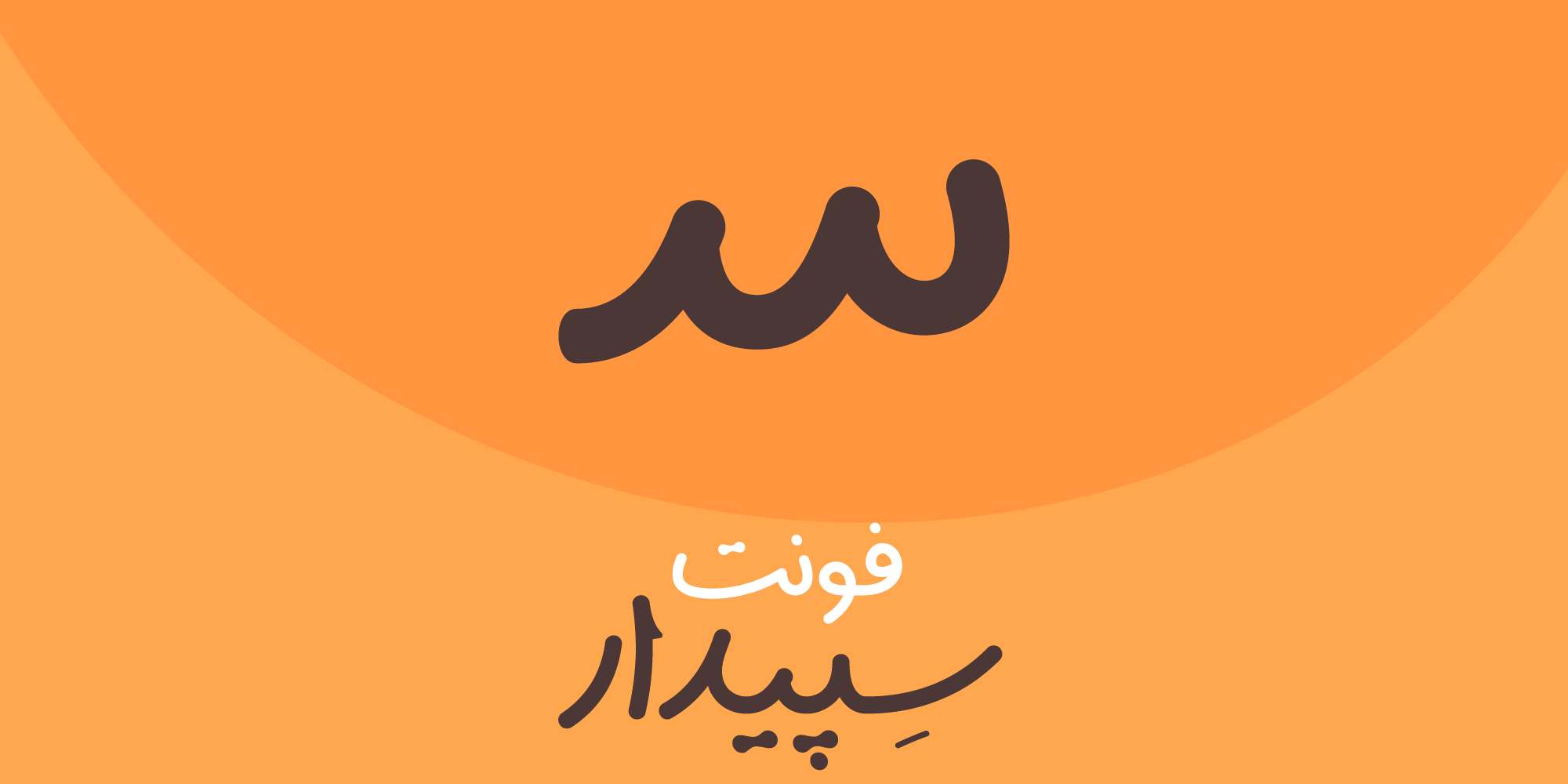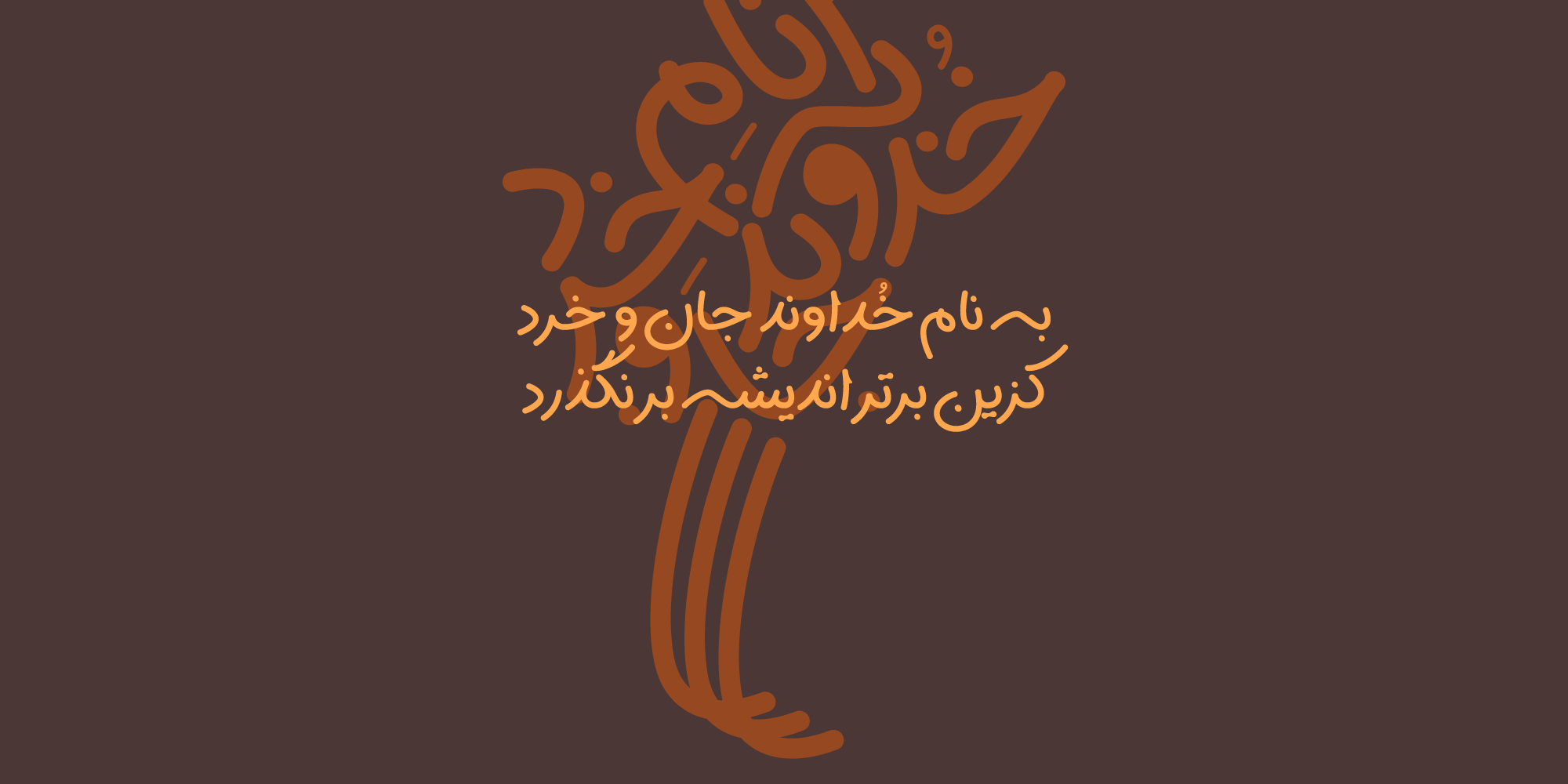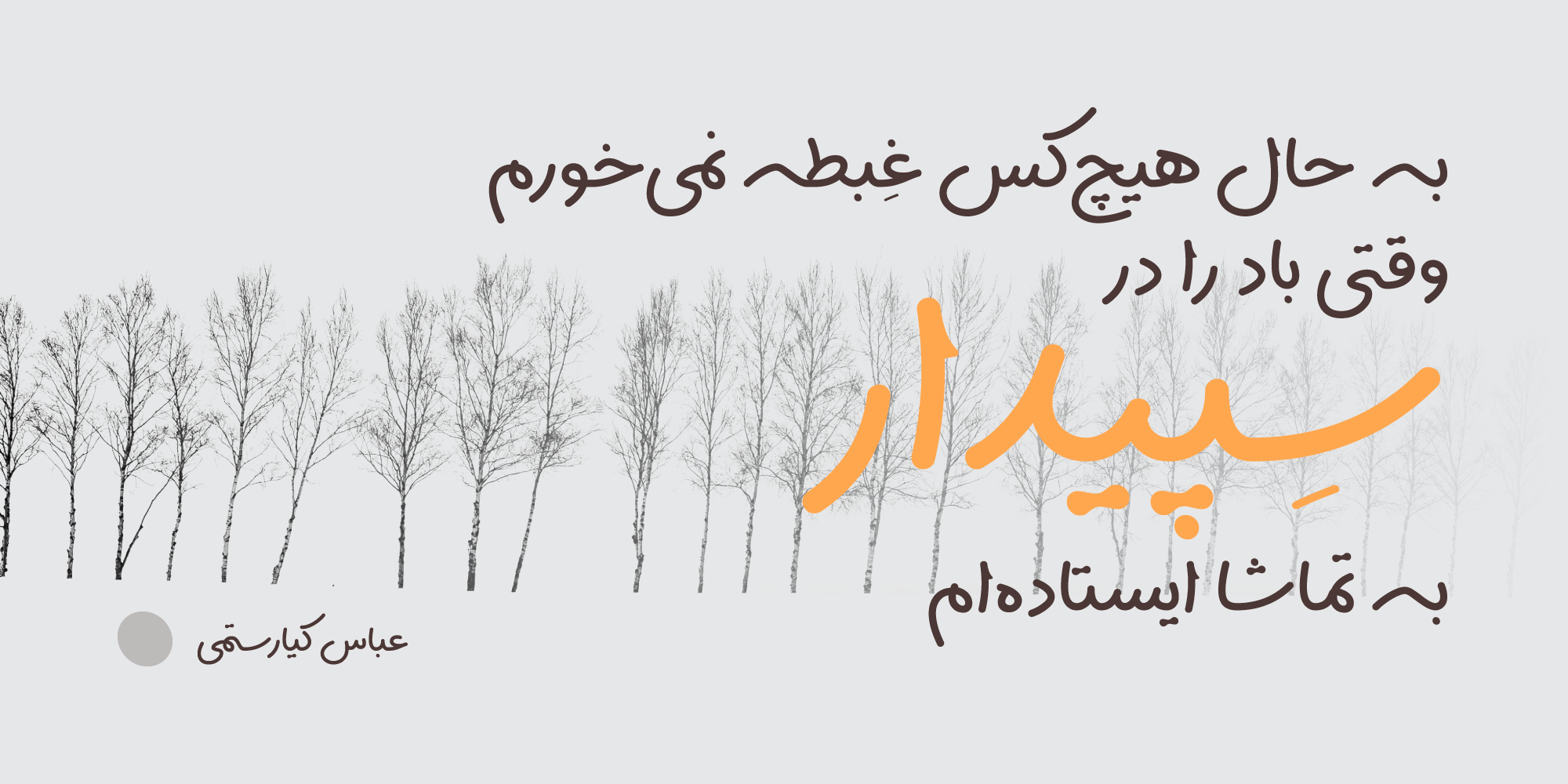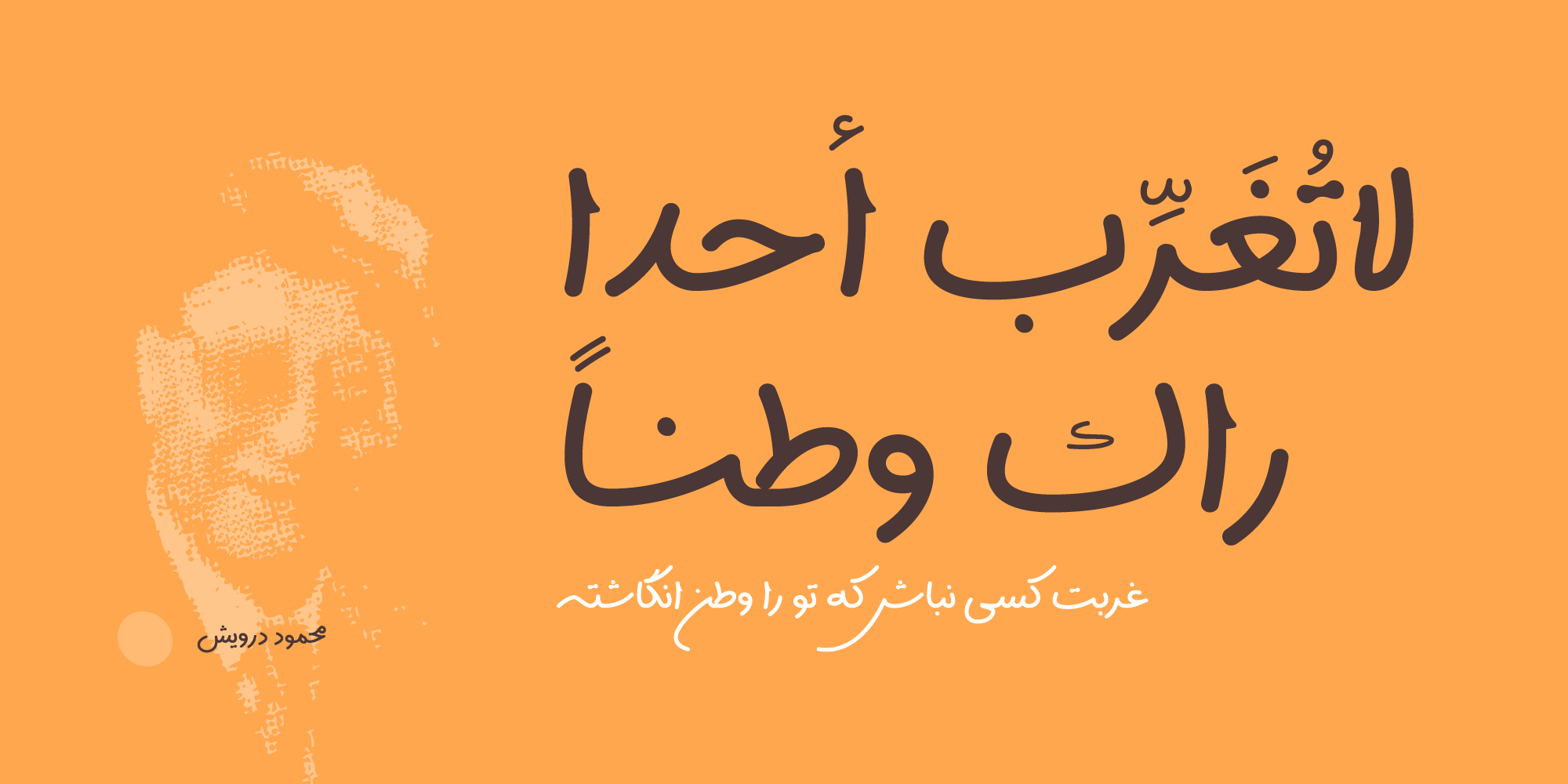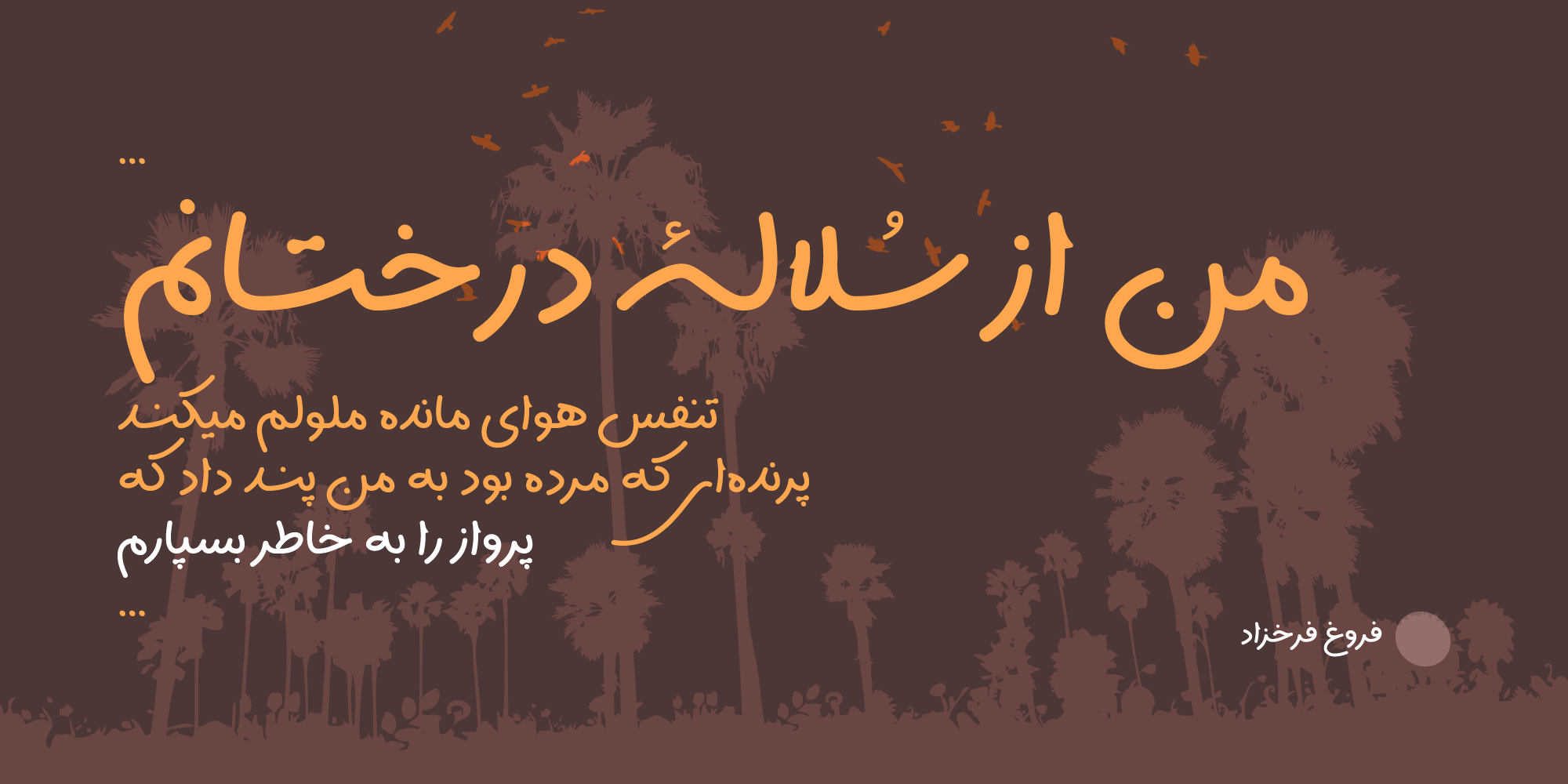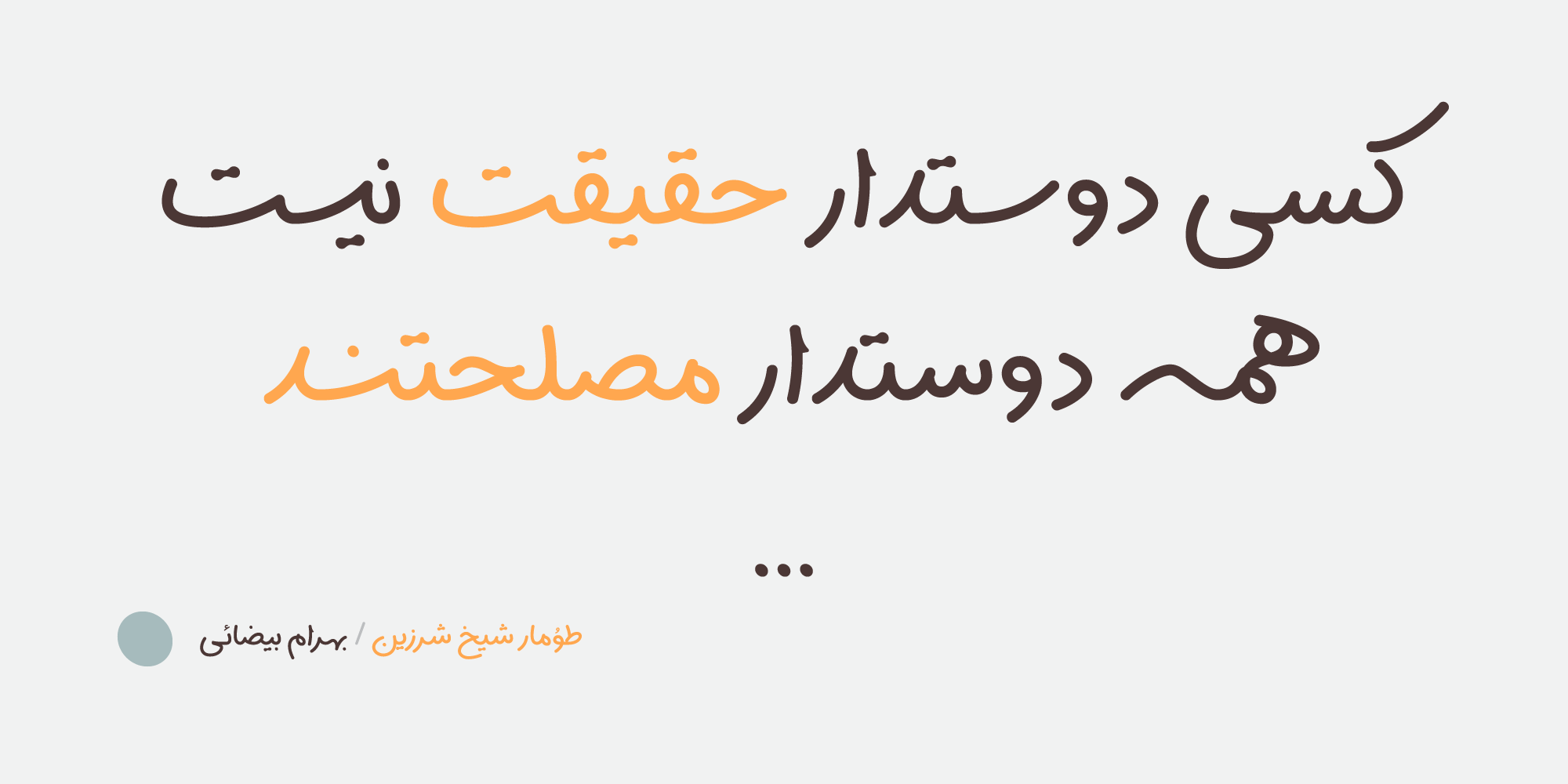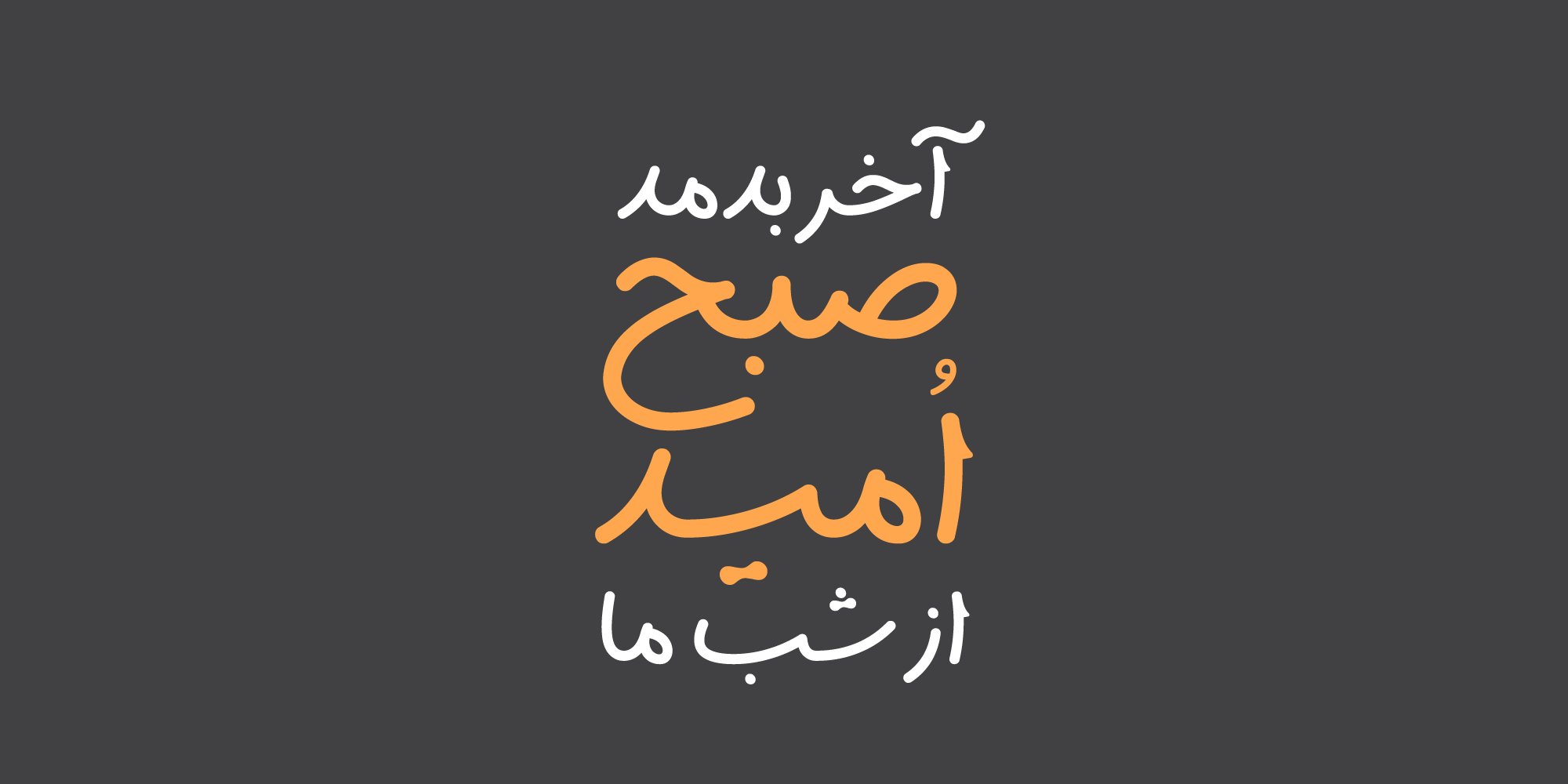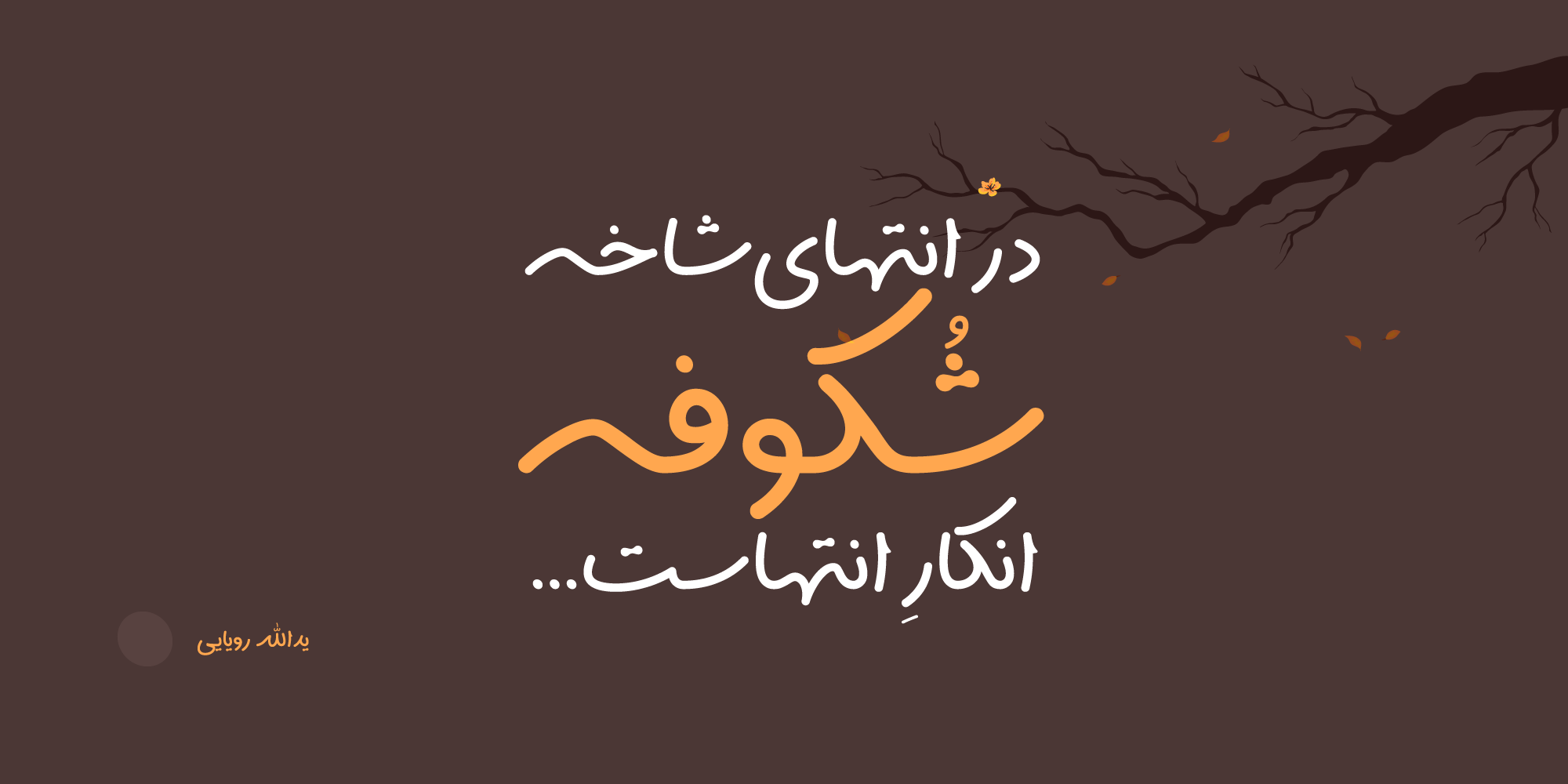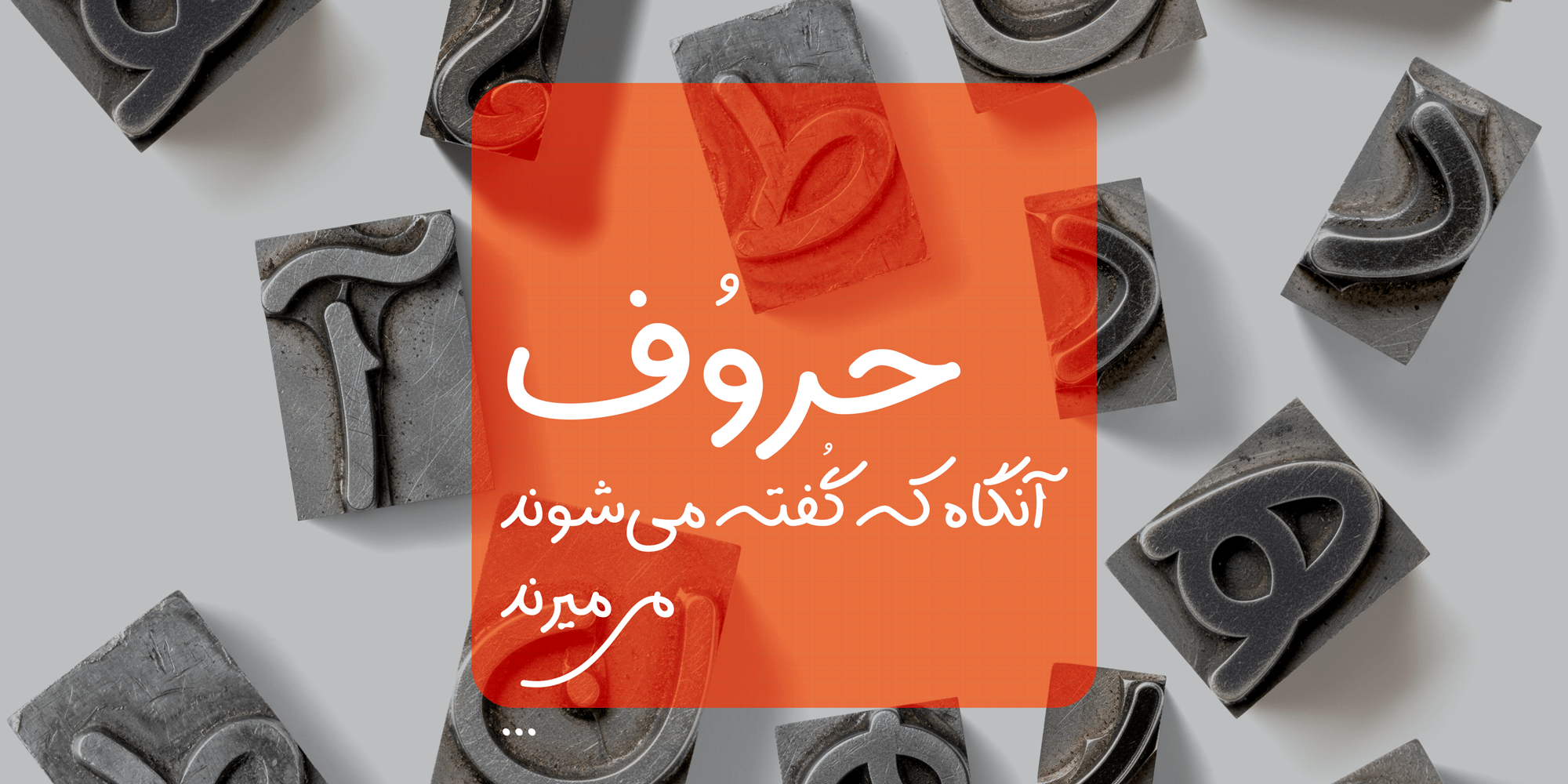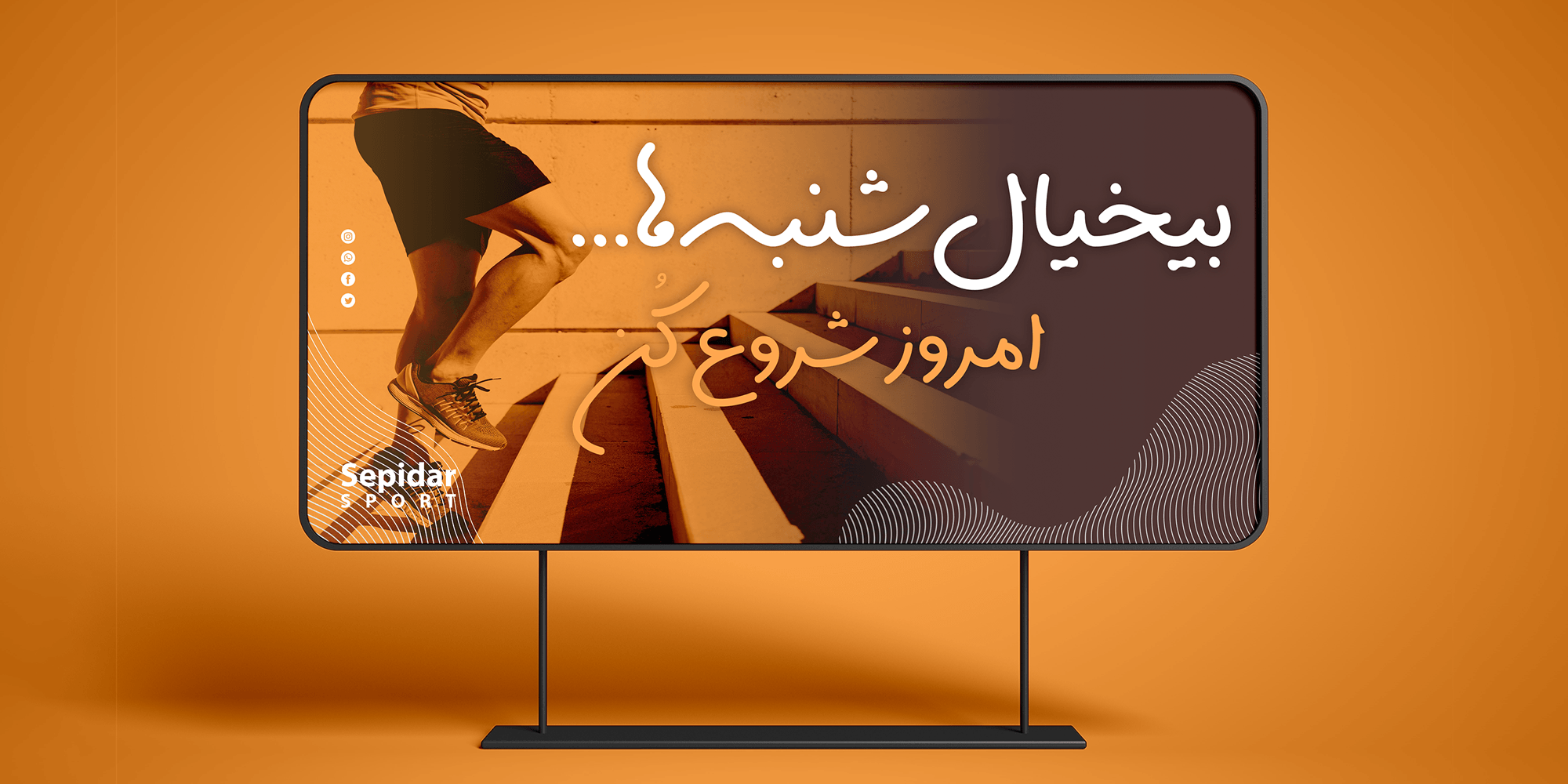
سپیدار شخصیتی منعطف و نرم دارد. از این رو مناسب برای استفاده در زمینههای گوناگون مانند شعارهای تبلیغاتی٬ تیترها و کلاً کلمات و جملاتی که مستلزم جور دیگر دیده شدن است میباشد.
سپیدار شخصیتی نمایشی دارد.
تنوع لیگچر و ترکیبات جایگزین
سپیدار برای تنوع در نوع نمایش حروف دارای لیگچرها و ترکیباتی است تا کاربر از فونت سپیدار به عنوان ابزاری جامع به مجموعهای از اشکال مختلف حروف دسترسی داشته باشد و بتواند بنا بر موضوع و حس و حال کاری که انجام میدهد ترکیب و چیدمان شخصی برای خود به وجود بیاورد.
وضوح و پشتیبانی از زبانهای دیگر
سپیدار در هر سایزی خوانایی و امکان استفاده را دارا میباشد.
از زبان عربی٬ کوردی و اردو با توجه به مجموعهای کامل از کلمات و اعراب و اعداد پشتیبانی میکند.
متولد ۱۳۵۵ تهران طراح گرافیک، تایپفیس، لوگوتایپ و کالیگرافر
شهرزاد اکبری، متولد ۱۳۷۰، دانش آموخته کارشناسی کامپیوتر نرمافزار. شهرزاد تجربه برنامه نویسی با زبانهای مختلف و همچنین تولید محتوا و طراحی برای چند استارتاپ را داشته است. او پس از آشنایی با «توسعه فونت» به عنوان ابزاری برای تلفیق هنر و علم برنامه نویسی به این حوزه علاقهمند شده و در آن مشغول به فعالیت شده است.